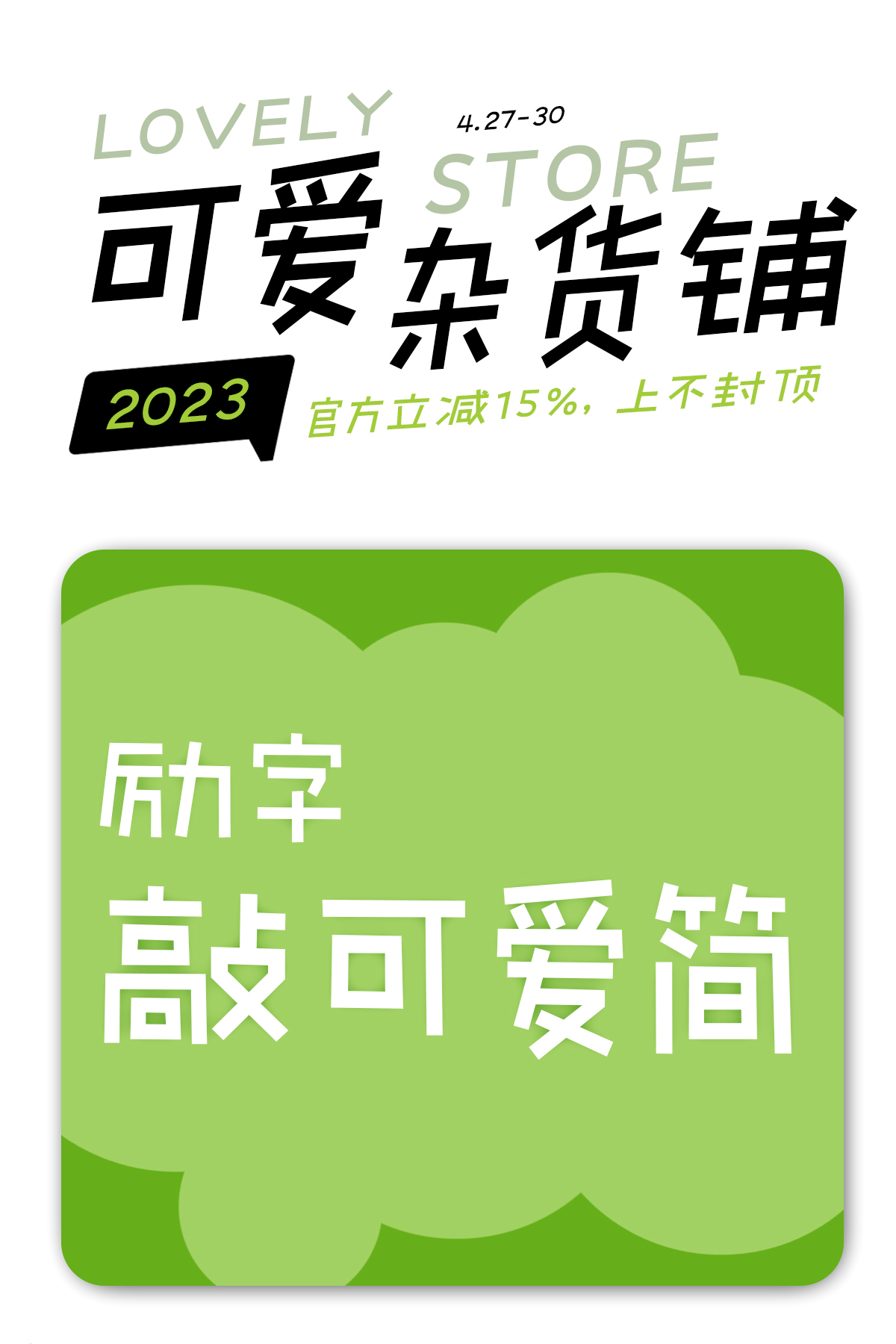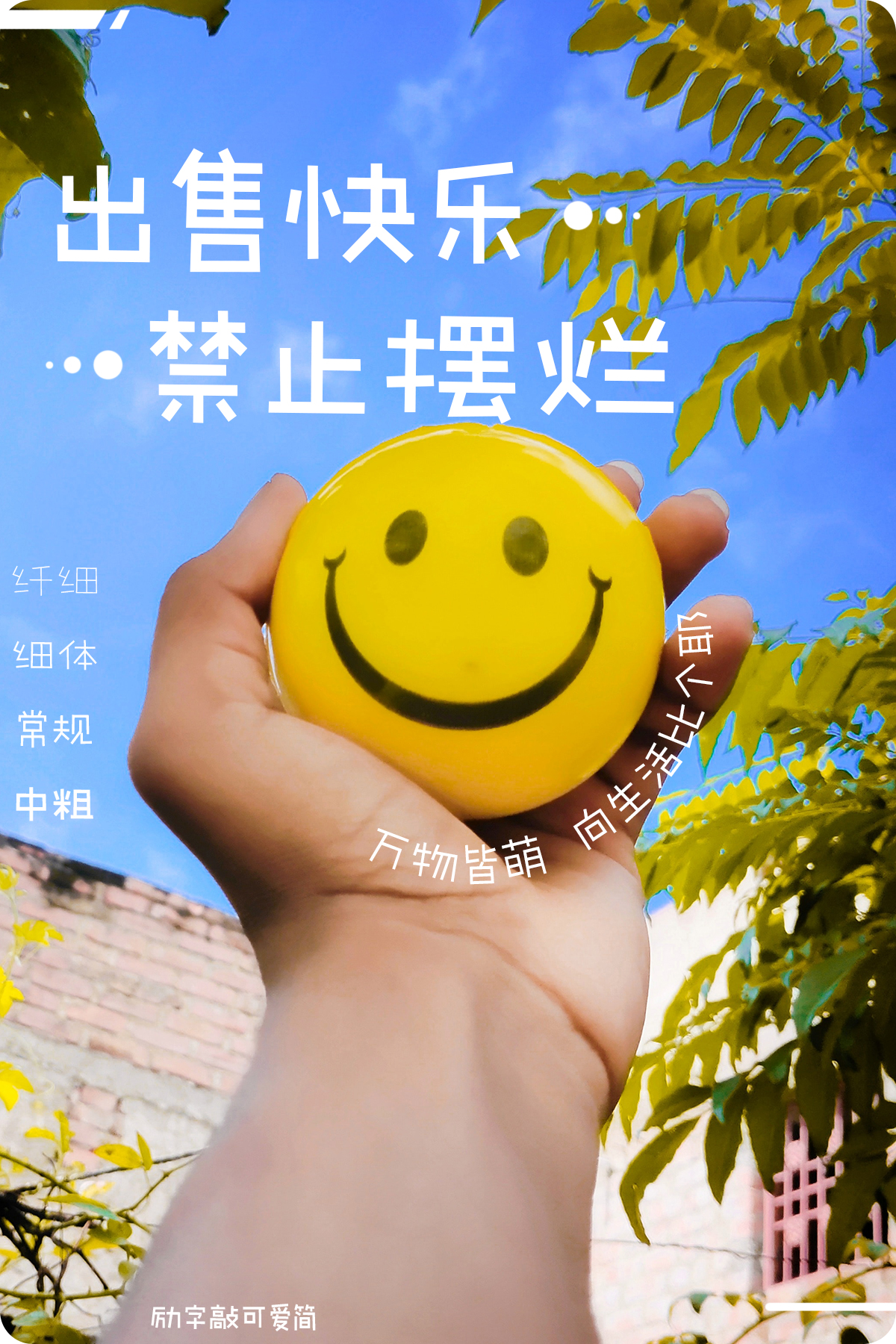
风靡中国零食行业、健康轻食的俏皮卡通字体——励字可变敲可爱
高速增长中.零食健康化已成市场的重要趋势。轻饮食、低 GI 饮食、 添加等观念正影响着零食行业发展的风向,休闲食品健康化趋势凸显,大健康已成为风口。今天推荐一款轻食健康零食的品牌ip以及包装宣传都需要一款深度匹配的字体——励字可变敲可爱简。
一款略带俏皮,充满趣味与想象的创意直线字。手写的圆润线条在保留辨识度的前提下,省略部分笔画,简单,明快的线条,独特的形式,营造用心书写的随性,让字体更具手绘感,带来手写的柔软和温暖。